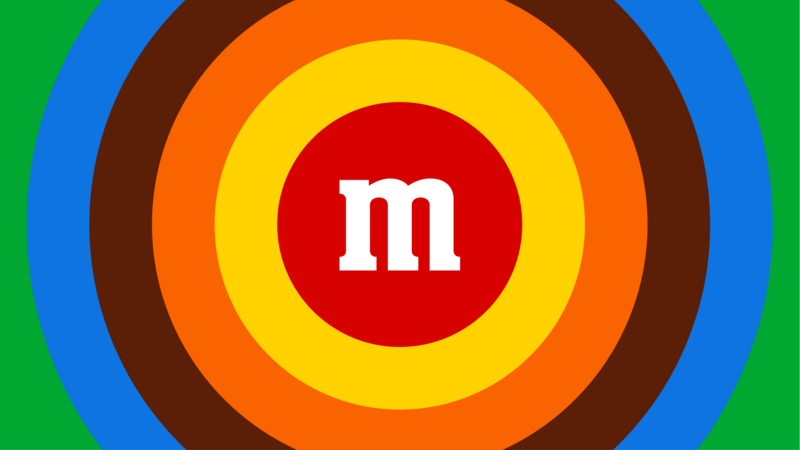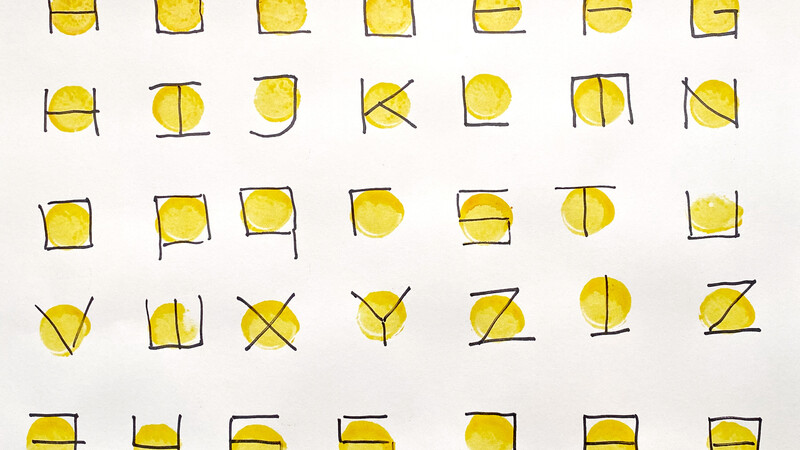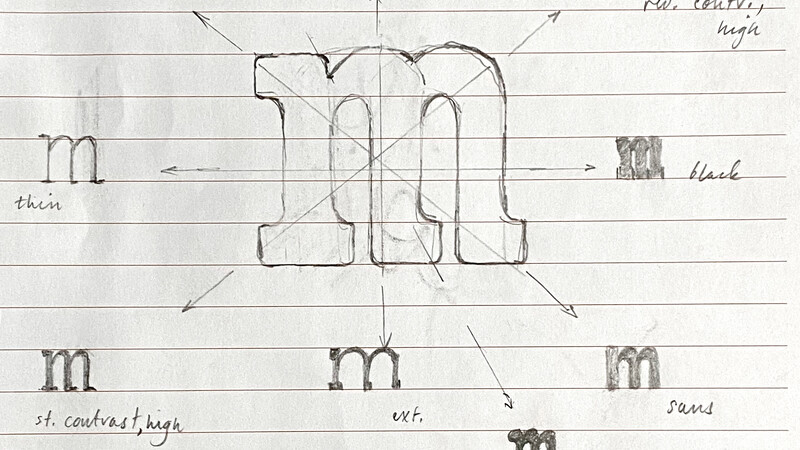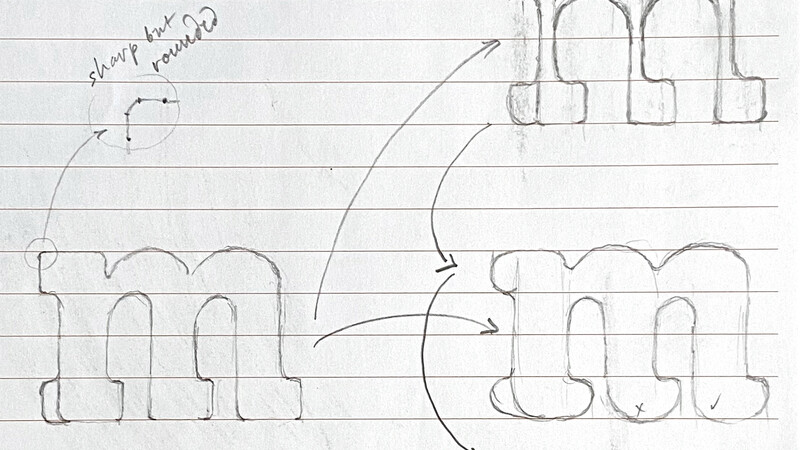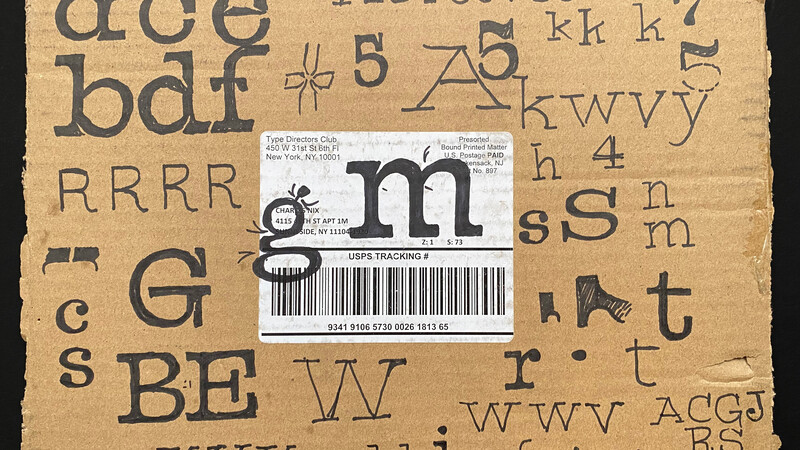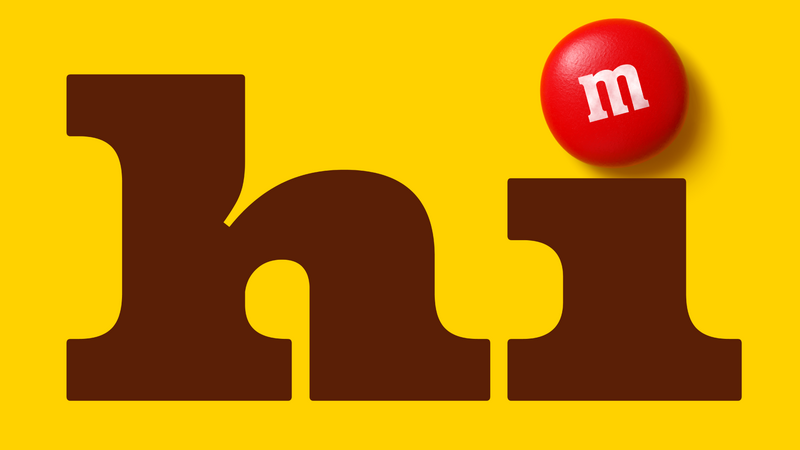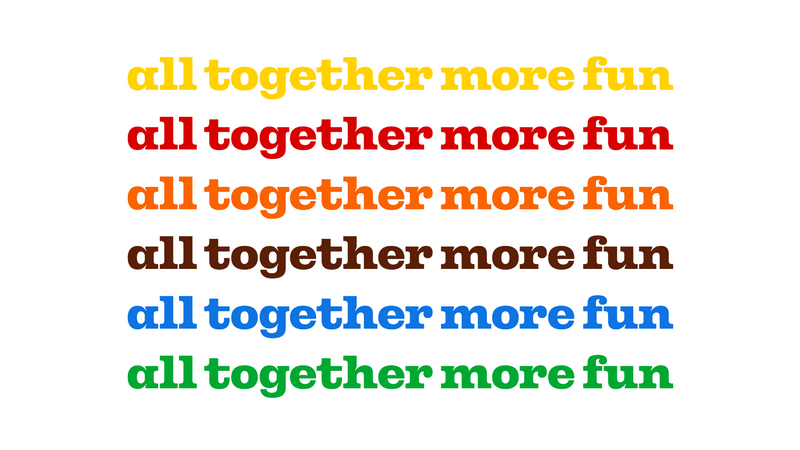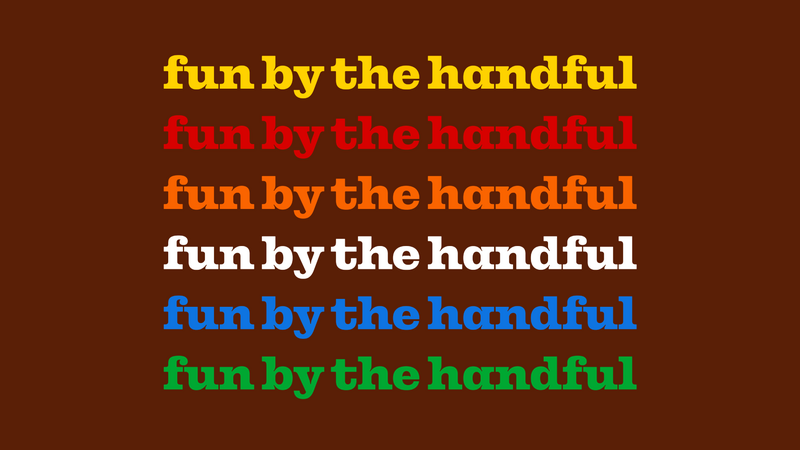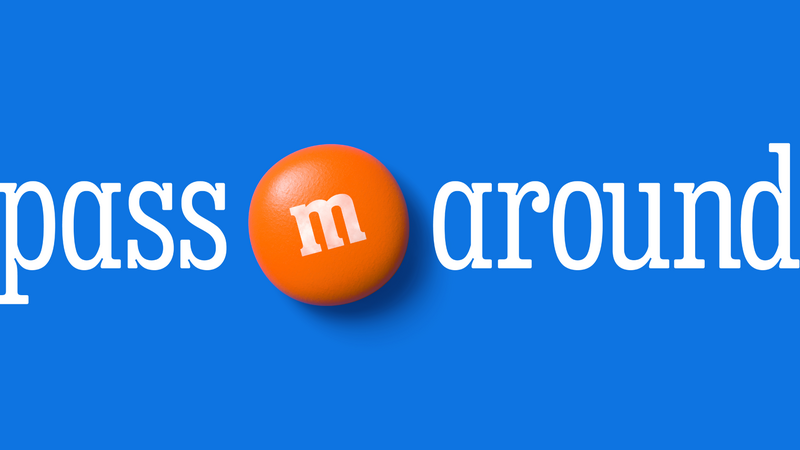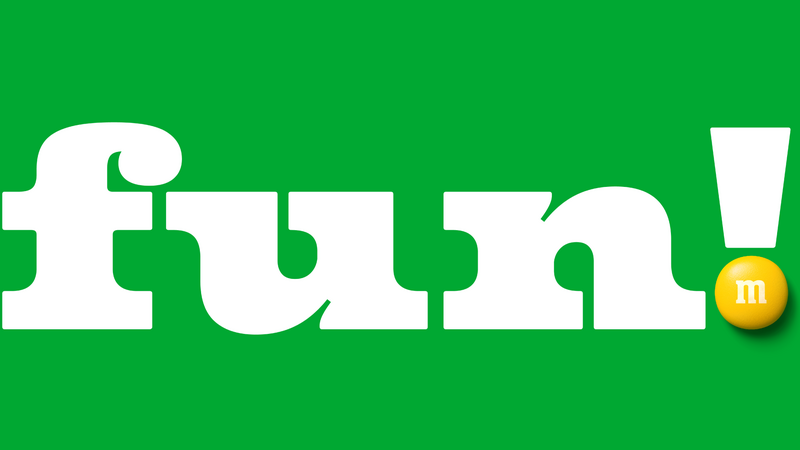
Fontes com foco na moda para a M&M.
A M&M’S® vem aproximando pessoas pelo mundo há mais de 80 anos. Neste ano, a icônica marca passou por uma reformulação, com o propósito renovado de criar um mundo em que todo mundo se sinta parte. Outras mudanças incluíram um novo visual e personalidades atualizadas para os famosos personagens de M&M’S, um tom de voz mais inclusivo e acolhedor, e uma nova fonte de chamar a atenção chamada All Together: uma família grande, calorosa, divertida e comunicativa.
Uma robusta e longeva relação levou a equipe de M&M’S e sua agência, Jones Knowles Ritchie (JKR) a escolher a Monotype para o primeiro projeto de design de fonte personalizado. O suporte linguístico global da Monotype também fez diferença. “A Monotype é uma marca tão grande, capaz de desenvolver fontes para diversas idiomas e mercados. Me senti mais à vontade trabalhando com um parceiro detentor dessa escala e consciência internacional”, disse a diretora global de identidade de marca e design da Mars, Steffi Marty.
“
Para mim, o momento do ‘arrá!’ foi quando vi os personagens revisados falando em suas vozes tipográficas. Dentro desta família há tanta expressão tipográfica que personagens tão diferentes quanto estes podem encontrar uma voz distinta. ”
Charles Nix, diretor criativo de tipografia.
Esboços dos estágios iniciais do projeto.
Para alimentar a colaboração, foi oferecida às equipes de design uma visão clara como guia. “Ao passo em que a marca M&M’S assume um propósito incrível, queremos que sua identidade reflita e apoie a comunicação de tudo isso. O objetivo da identidade é viver o propósito, ser mais habilidosa com o meio digital, e fazer do propósito onipresente em tudo que fazemos”, explicou Marty. A equipe de design da JKR colaborou com o diretor criativo de tipografia Charles Nix e o designer tipográfico Juan Villanueva para harmonizar a tipografia com a nova identidade visual da marca.
O primeiro imperativo foi personalidade: a nova fonte deveria gritar “M&M’S” logo de cara. Nix e Villanueva conseguiram isso com um estilo de serifa quadrada grande, rechonchudo, cheio de personalidade que lembrava o antigo visual de M&M’s e reforça o espírito sagaz e brincalhão da marca. A incorporação de detalhes alegres, como ink traps na forma de sorrisos e terminais arredondados semelhantes ao doce, aumentava ainda mais o fator diversão.
Outro elemento essencial foi a flexibilidade. All Together, a fonte, seria usada em tudo: das embalagens aos vídeos e textos digitais. Isso levou à decisão de utilizar um software de fontes variáveis, que incorpora uma ampla gama de variações de largura, peso e estilo dentro de um único arquivo de fonte. As fontes All Together Sans e All Together Serif representam um enorme espectro de design capaz de criar fontes vivas para textos pequenos e densos de embalagens, bem como cabeçalhos e animações carismáticas.
“Para uma marca do porte de M&M’S, é preciso flexibilidade com a fonte”, explicou Lilia Quinaud, designer sênior da JKR. “Ter uma família sem serifa e serifada proporciona a flexibilidade necessária para mostrar tanto informações funcionais quanto informações divertidas, em destaque, que chamem a atenção. Começamos com a All Together Serif, inspirada pelos desenhos e serifas do logotipo. É por isso que ela remete à M&M’S logo que se bate o olho.”
Com mais opções de fontes, os designers têm liberdade para combinar e contrastar formas para chegar ao visual ou emoção perfeitos para casar com a mensagem. “As famílias All Together Sans e Serif não são uma série de instâncias estáticas. O espectro de possibilidades cria um espaço de design novo e multidimensional com oportunidades para criação de visuais mais fluidos e expressivos”, disse Nix.
Fontes variáveis são perfeitas para representar a voz de cada um dos mascotes atualizados também. “Para mim, o momento do ‘arrá!’ foi quando vi os personagens revisados falando em suas vozes tipográficas”, comentou Nix. “Dentro desta família há tanta expressão tipográfica que personagens tão diferentes quanto estes podem encontrar uma voz distinta.” A nova tipografia de M&M’S reforça de fato o objetivo do rebranding: estamos todos juntos (All Together), e nossa diversidade traz consigo força.
“A nova e inclusiva fonte de M&M’s: All Together. ”